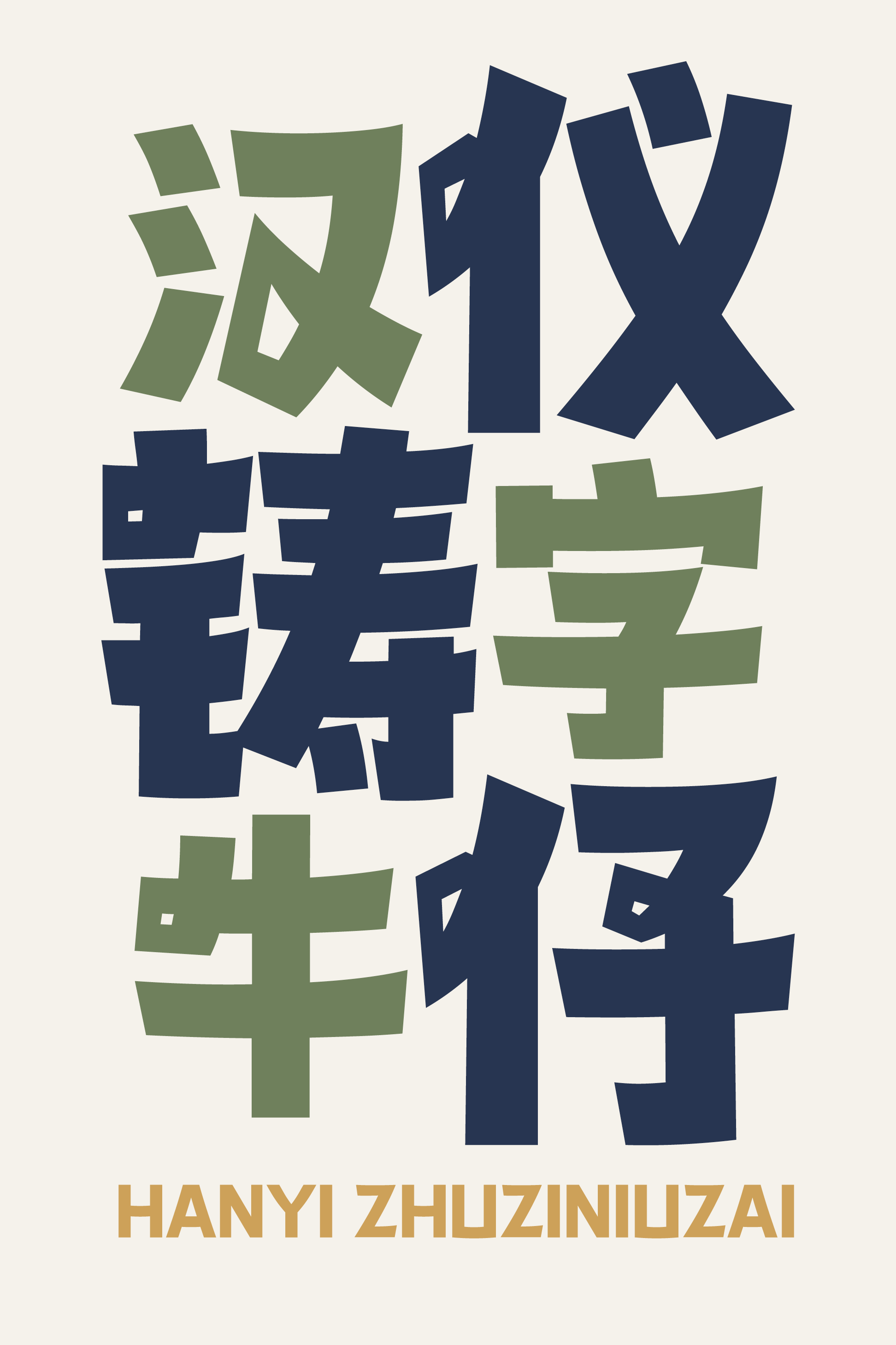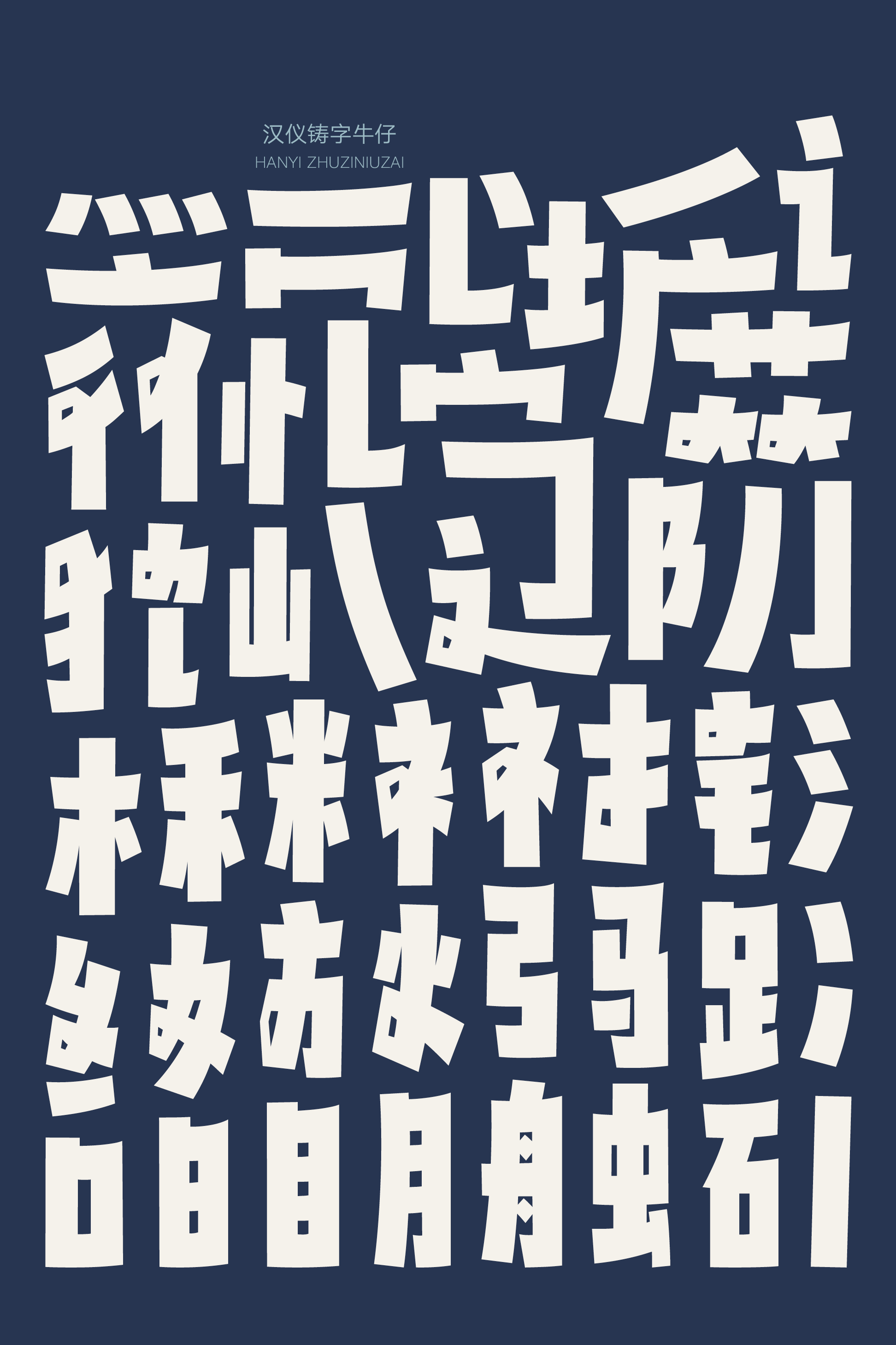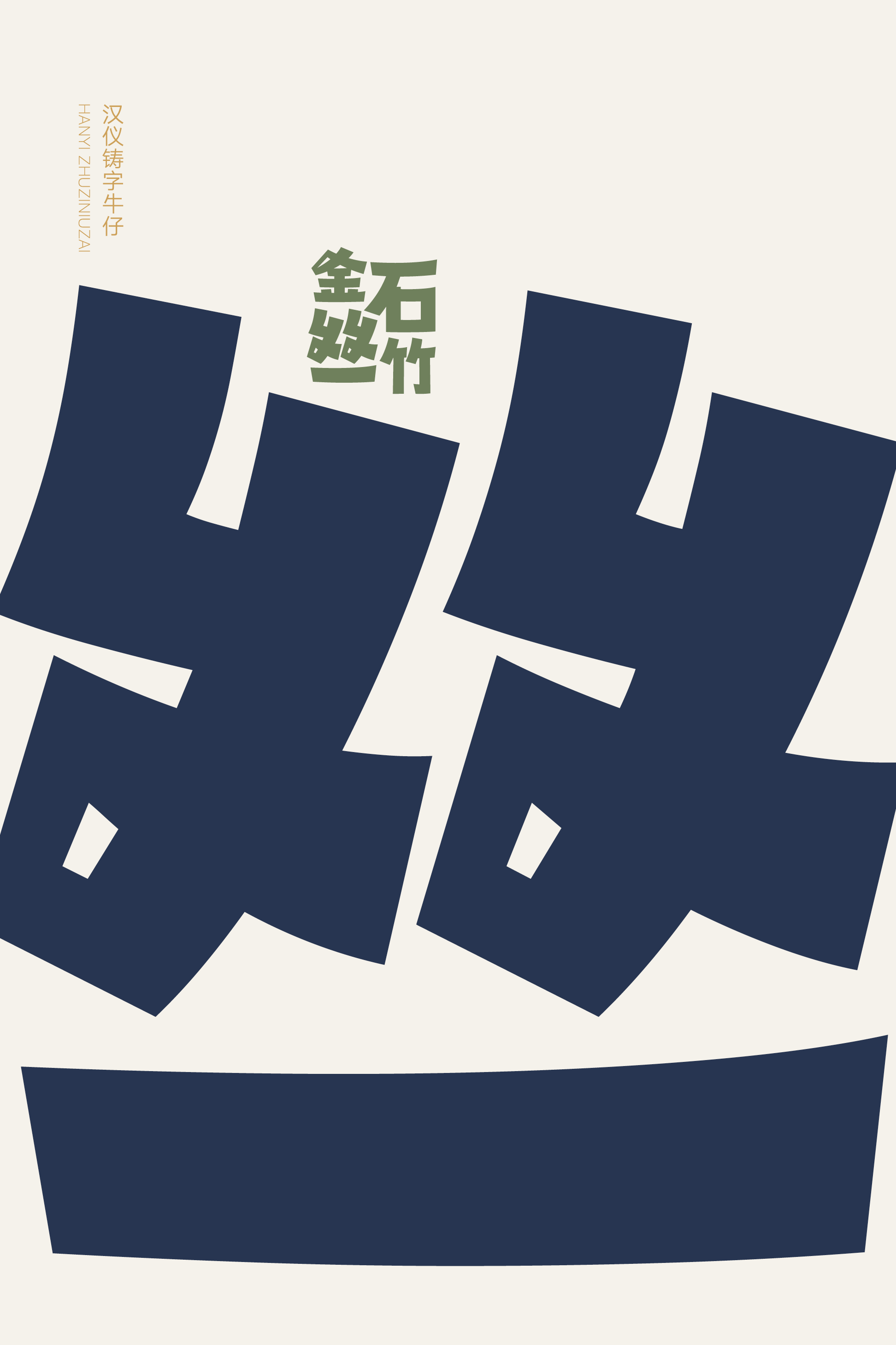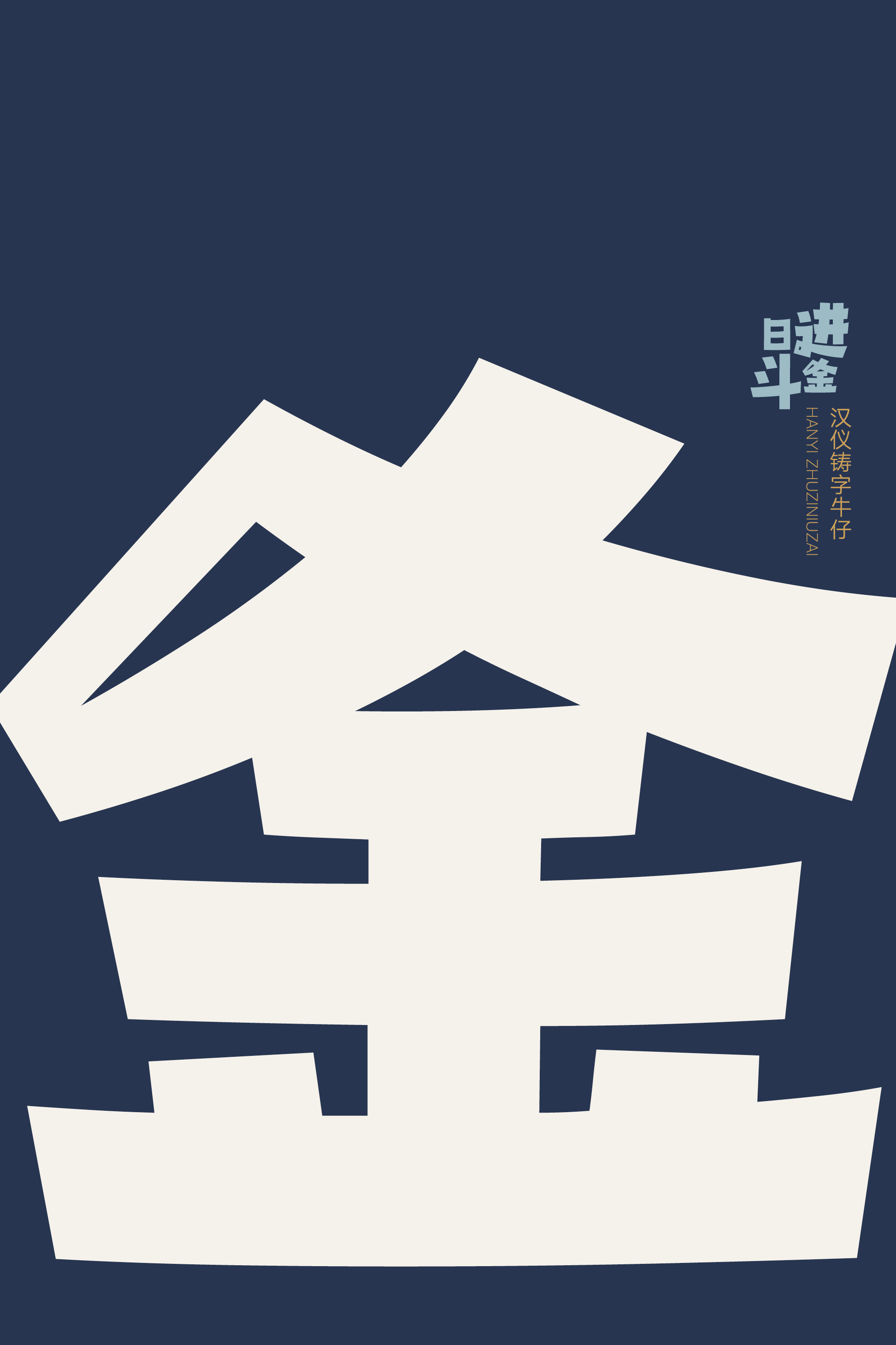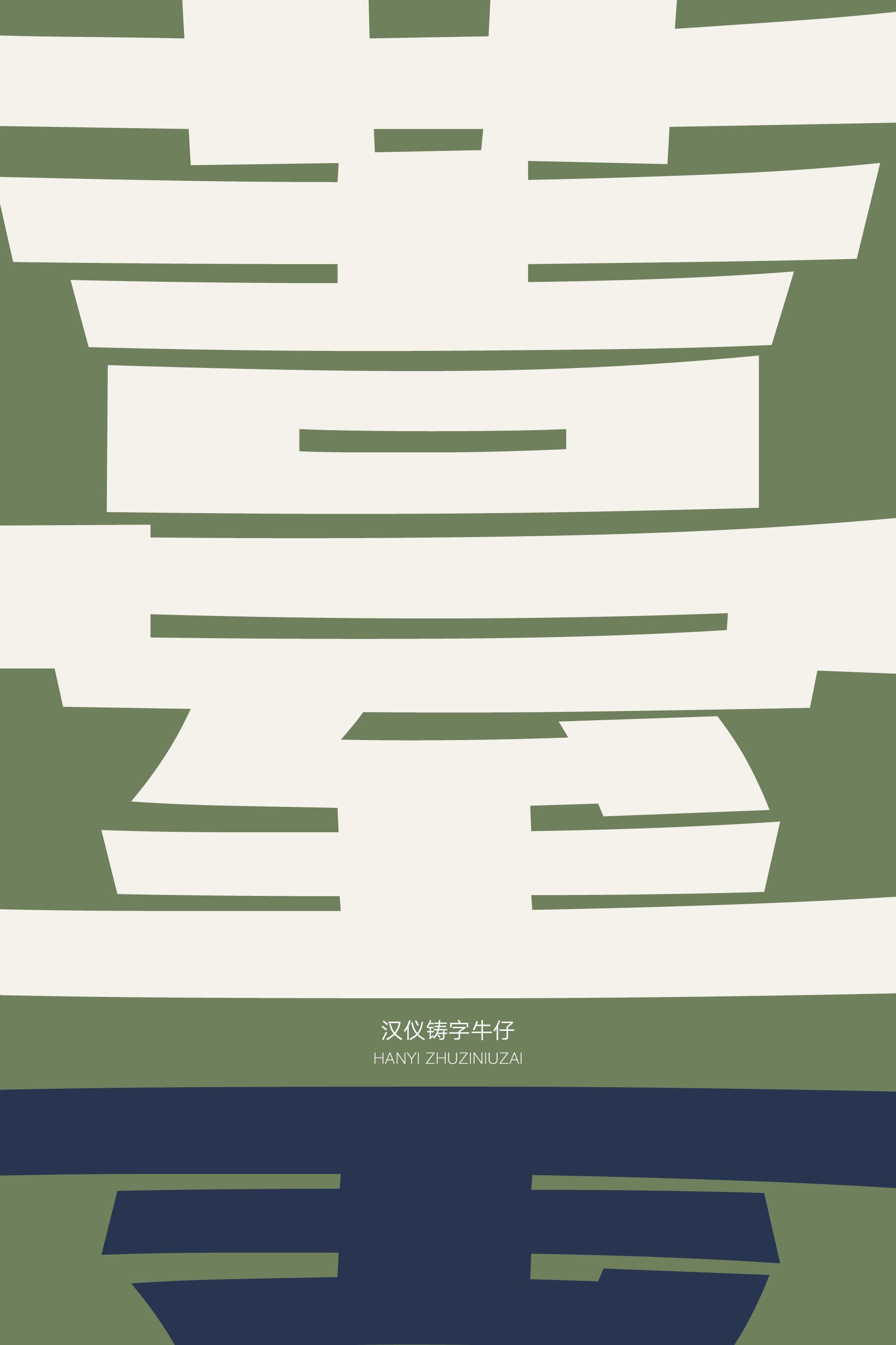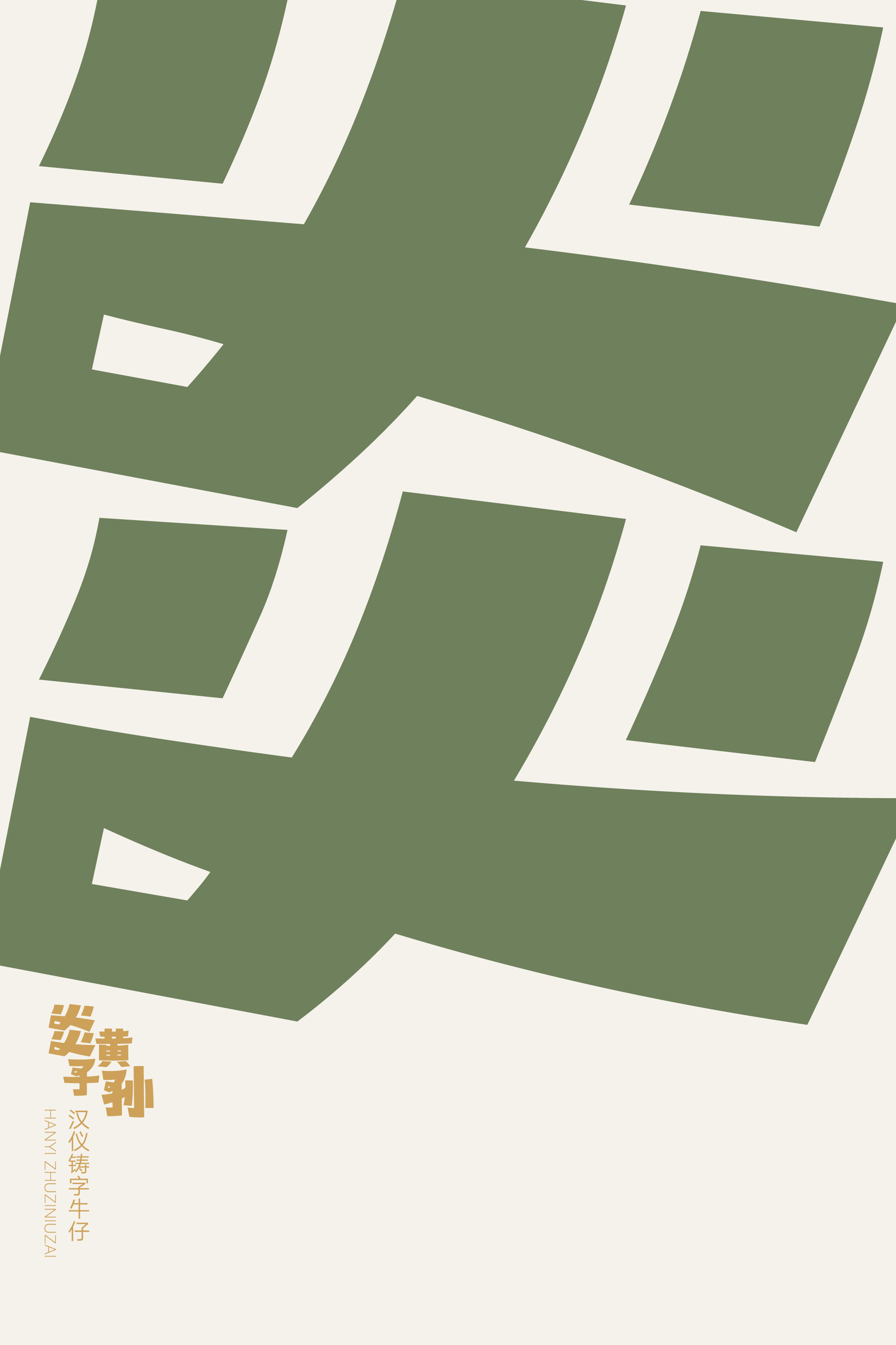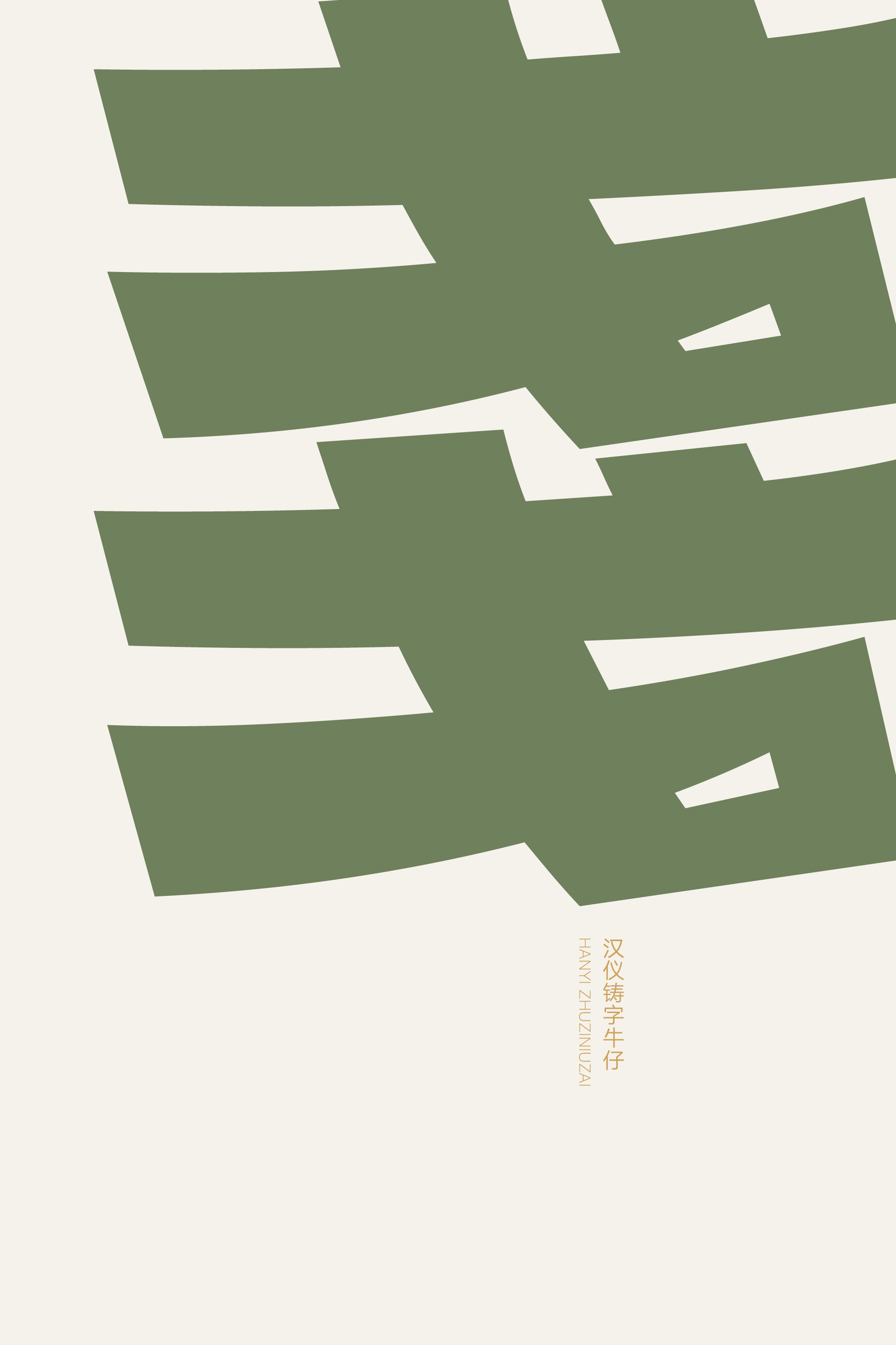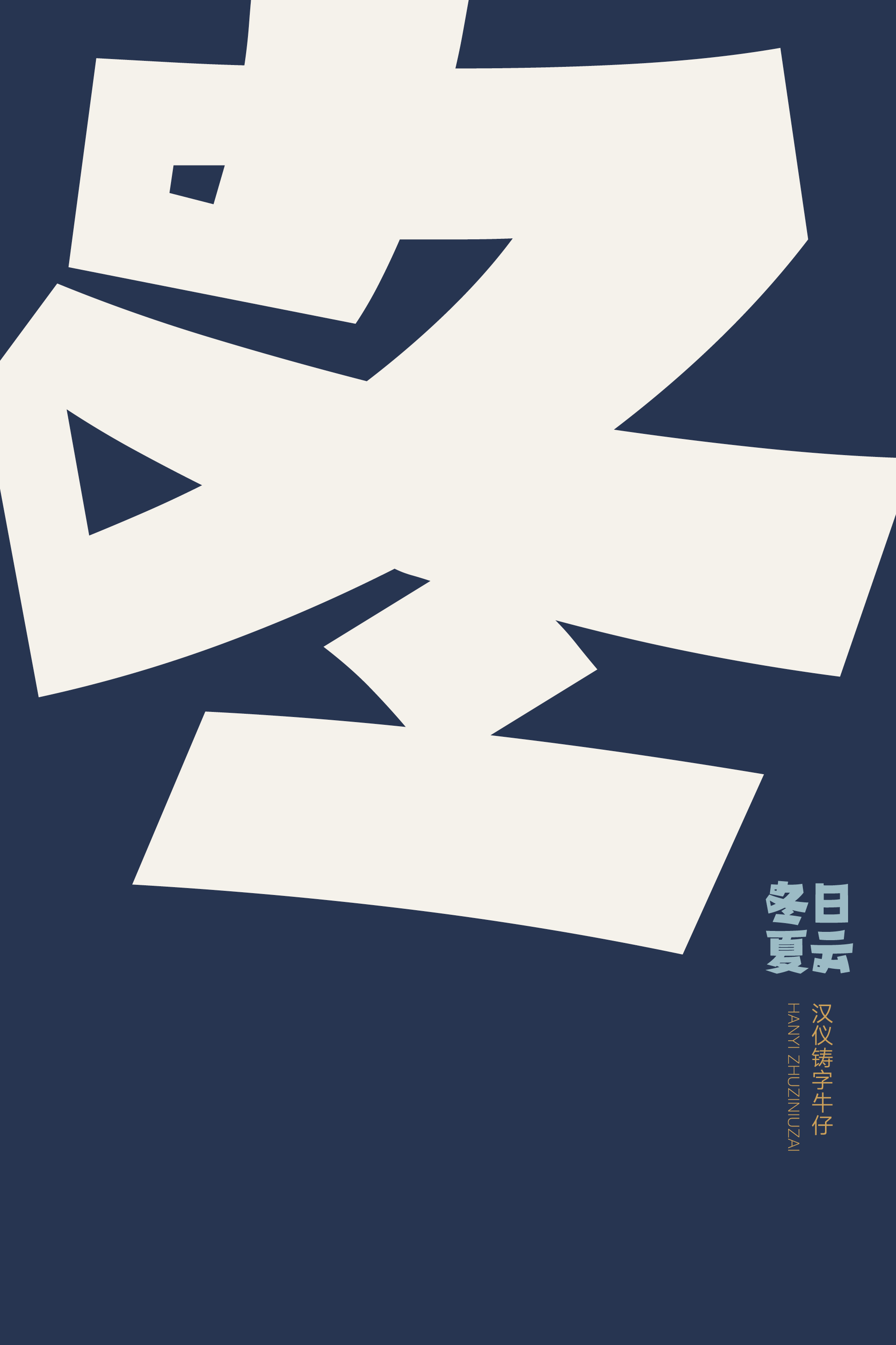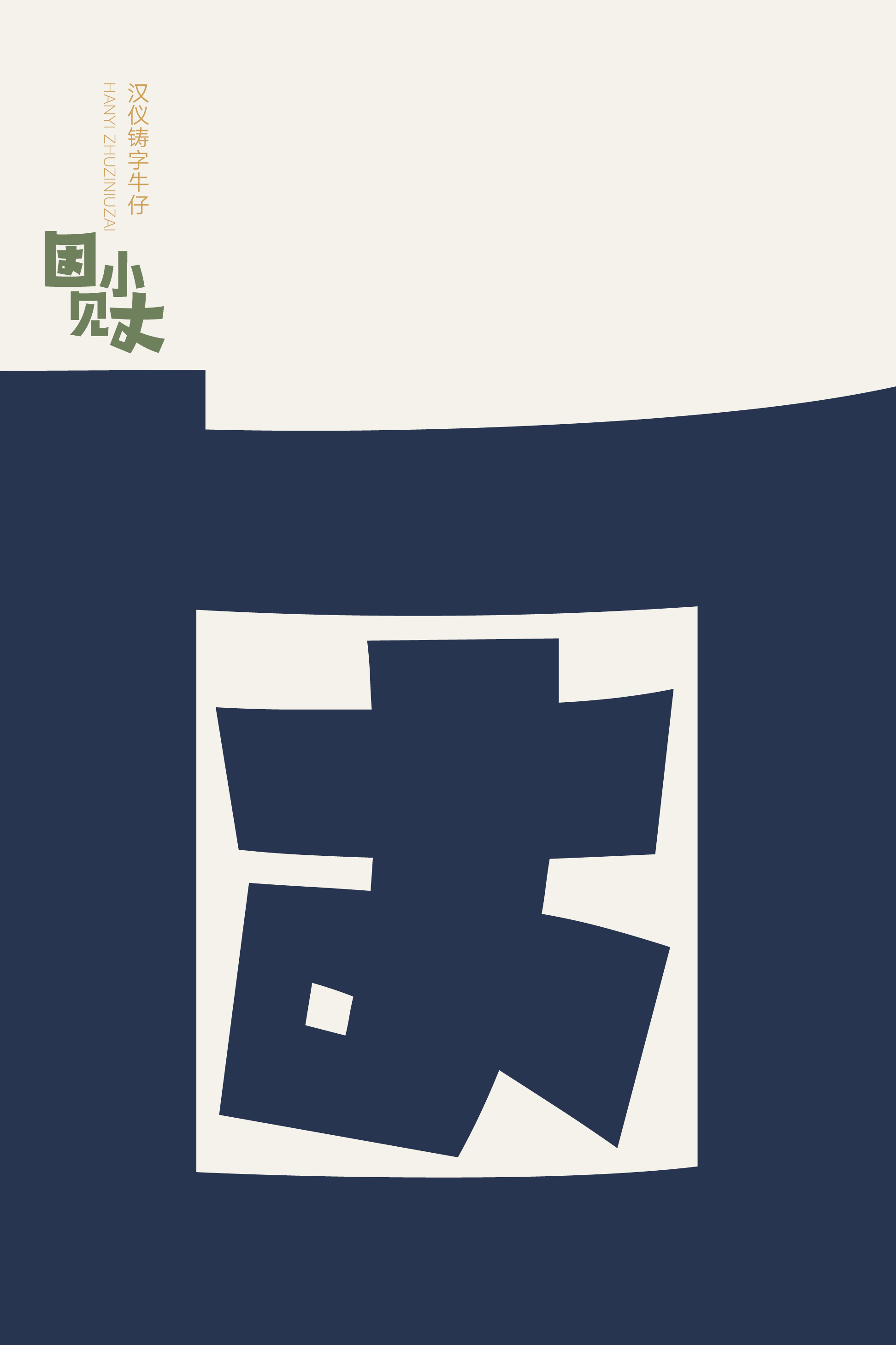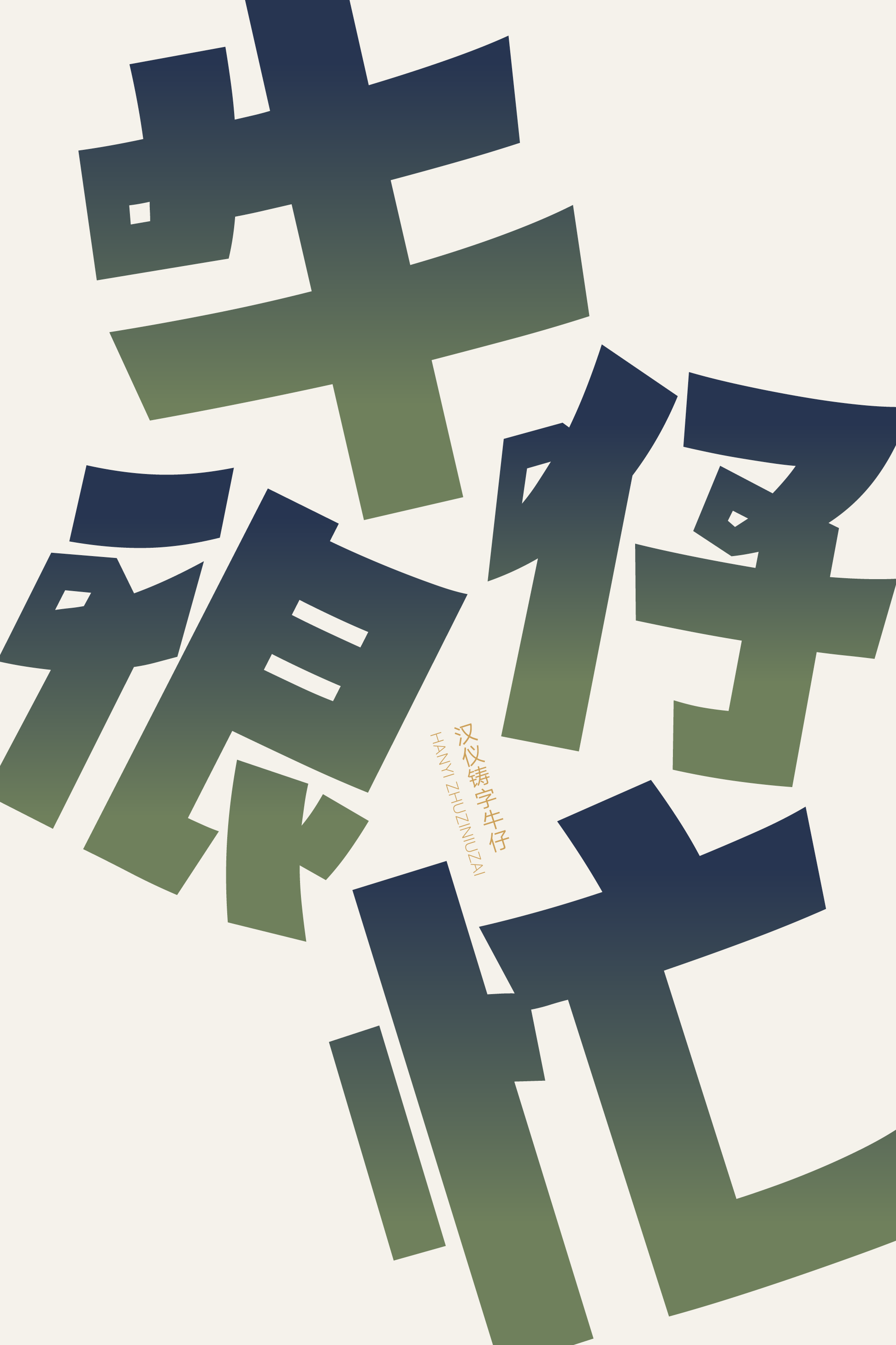
汉仪铸字牛仔
——嘿,老伙计!
——瞧瞧,这不是汉仪铸字牛仔吗?
硬朗的外形、方硬的直线和蓄力的曲线、牛仔标志性的套索,一看就知道是自由奔放的汉仪铸字牛仔。这款充满奇趣的标题字体由铸字社创作,适合应用于品牌包装、电商广告、影视游戏等多种使用场景,既有粗重笔画带来的力量感,又有装饰设计带来的趣味性,鲜活地以字体塑造出牛仔形象。
字形方而硬朗。
笔画粗重:竖笔方直简洁,横笔曲线蓄力,弧形笔画的曲线也充满力度。
笔画连带处理是牛仔标志性的套索。
西文部分造型简洁,保留了横笔的蓄力曲线和竖笔的方直,省略了牛仔套索的装饰。